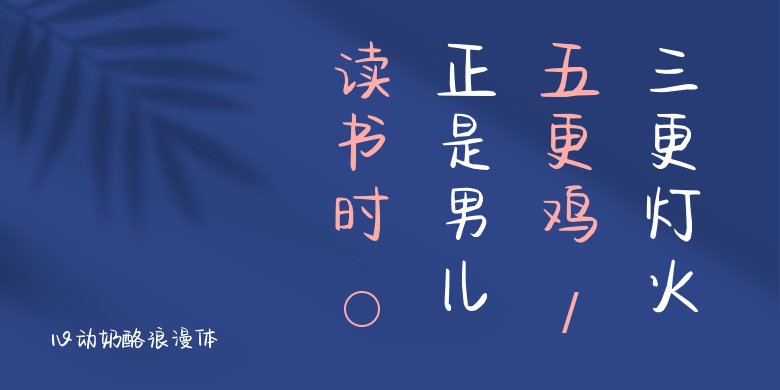
心动奶酪浪漫体
心动奶酪浪漫体,这款字体结构工整、笔画清晰,兼顾美观与易读性,适用于标题、正文、海报、包装、LOGO 等多种场景。字形优雅稳定,风格百搭耐看,适配日常排版与创意设计,让文字呈现更舒适、更具质感。心动奶酪浪漫体一笔一画,皆是细节,以均衡的比例、流畅的线条打造舒适视觉体验,字形端正大气,风格简约现代。无论是商业设计、品牌宣传还是日常排版,都能轻松驾驭,让文字更有格调与力量。心动奶酪浪漫体字体下载。